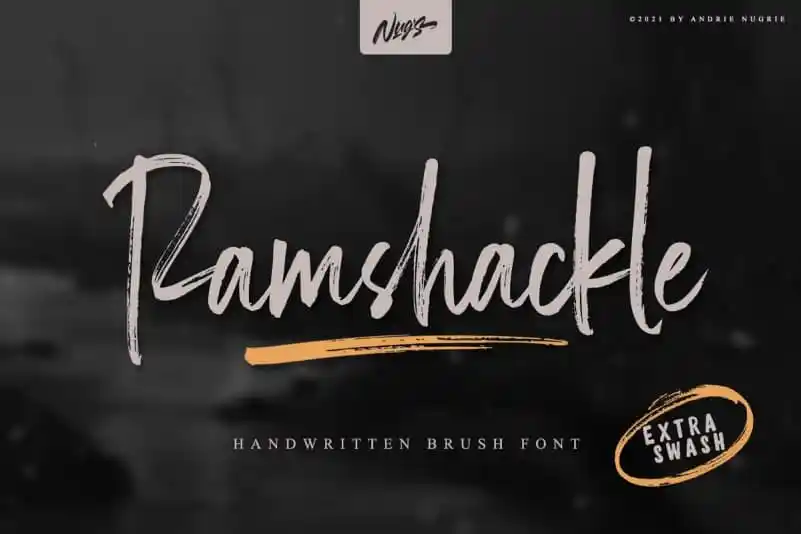
Ramshackle Brush Font – Download Grátis
Ramshackle Brush Font é uma fonte brush que oferece um estilo relaxado e fluente. Suas tramas suaves e fluidas são incrivelmente versáteis, adaptando-se a diversos tipos de design, elevando-os ao topo. Esta fonte brush moderna apresenta belos traços naturais perfeitos para criações como logotipos, panfletos, produtos, roupas, embalagens e muito mais. Ideal tanto para designers iniciantes quanto profissionais, esta fonte é uma ótima escolha para quem procura um estilo autêntico e natural sem perder em qualidade ou versatilidade. Experimente ela para dar vida a suas criações de design.